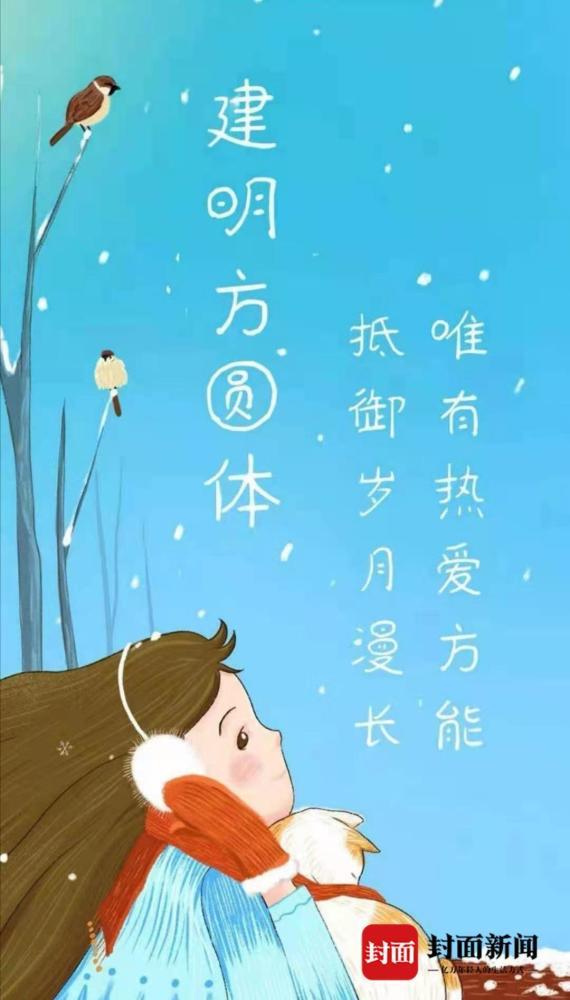
陈建明,四川南部县人,字体设计师。这样的设计师,在中国可谓为数不多。
十年前,他为北大方正电脑系统设计了“童体字”;十年后的今天,5G时代来了,他又为智能手机书写了15款字体。2月1日,封面新闻记者获悉,目前已有7款手写字体在小米、华为等智能手机上与用户见面,其它款式手写字体正在测试中。
童真童趣,“童体字”进入方正字库
陈建明从小就喜欢写字,无论是读书,还是工作期间,天天都要写几篇大小字,是中华全国钢笔、圆珠笔书法研究会会员,四川省硬笔书画家协会理事。紧张的工作之余,陈建明一心扑在“写字”上。“一个个方块汉字能不能写得更有趣一些哦?”有一次一位好友来访,陈建明边写字边让他提意见,好友想了半天,才说这些书法作品看起来气势充足,但无趣味,都是一些没有个性化的方块。朋友的意见一直让陈建明难以释怀,汉字能不能写得像漫画一样,让人发笑,让人捧腹,充满童趣。
结合自己的长处,陈建明开始自创一种新的字体,适度夸张和变形,字体圆润洒脱,极富童趣和美感,尽显童真童趣,他把这种字体称为“童体字”。可以广泛应用于广告、卡通、QQ聊天、报纸印刷等等。2008年,陈建明和方正字库签约,按“北大方正”提供的专业字模纸片,在上面书字常用的5000多个汉字,规范书法家书写的随意性,经过编码后就可以将书法作品变成电脑可以识别的字体。
十年间,陈建明的“童体字”已经走进千家万户的电脑,一看就笑的字体,也许你正在使用咧!
书写邀请函,刷屏企业家朋友圈
2018年11月20日,四川省民营经济健康发民大会召开,1520位参会企业家及单位,见证了我省民营经济发展史上最重大的会议。“熊猫、竹子、竹简......”那个别致的“网红熊猫竹简”邀请函刷屏企业家朋友圈。这封“邀请函”的全文正是陈建明所写。
为达到既精致,又突出四川元素,这份邀请函耗费了大量心思才最终呈现。据介绍,大会总共收到10多种邀请函设计方案。最终,这款“竹文化+大熊猫文化”的竹简设计方案,成功“抢戏”,竹简长80厘米,宽24厘米,展开后可看到邀请函全文。陈建明写了4种字体,最后选中了行楷。他还在广告公司设计的基础上进行升华,在左上角烙上中国印,左下角烙是“治蜀兴川”印。
个性与色彩,已有多种“手迹”进入手机
这封别致的竹简邀请函用的“建明行楷书”,十来年时间,陈建明陆陆续续设计出15种风格各异的字体,建明隶书、建明熊猫体、建明舞体、建明风骨体、建明方圆体等15种字体。这种个性化字体在多元化社会里写出汉字的个性,“充满个性和时代色彩”。
随着5G时代到来,智能手机的出现,人们对个性化的字体要求越来越高。去年下半年,陈建明和北京方正手迹数字有限公司签约,推广陈建明的手写字体。业内专家称,将个人书法用品开发成电脑识别的字库非常罕见。
陈建明受邀在北京写了3个多月的字。和当年的“童体字”一样,写在专业字模纸片上,方便电脑识别编码。
陈建明告诉封面新闻记者,字体推广更多是一种公益性的,他并不能从中获得多少收益。“‘方正字库’主要用在电脑上,‘方正手迹’主要用在智能手机上,智能手机也有款式不一样的手写字体。”
受制于多种原因,各种字体面市时间并不一致。截至2月1日,建明字体在小米上已有7款手机、华为手机上有3款,OPPO手机上有一款。“自己喜欢中国文化,喜欢个性化的中国汉字书写。看到朋友手机使用自己设计的字体,那是一种莫大的满足。”(受访者供图)